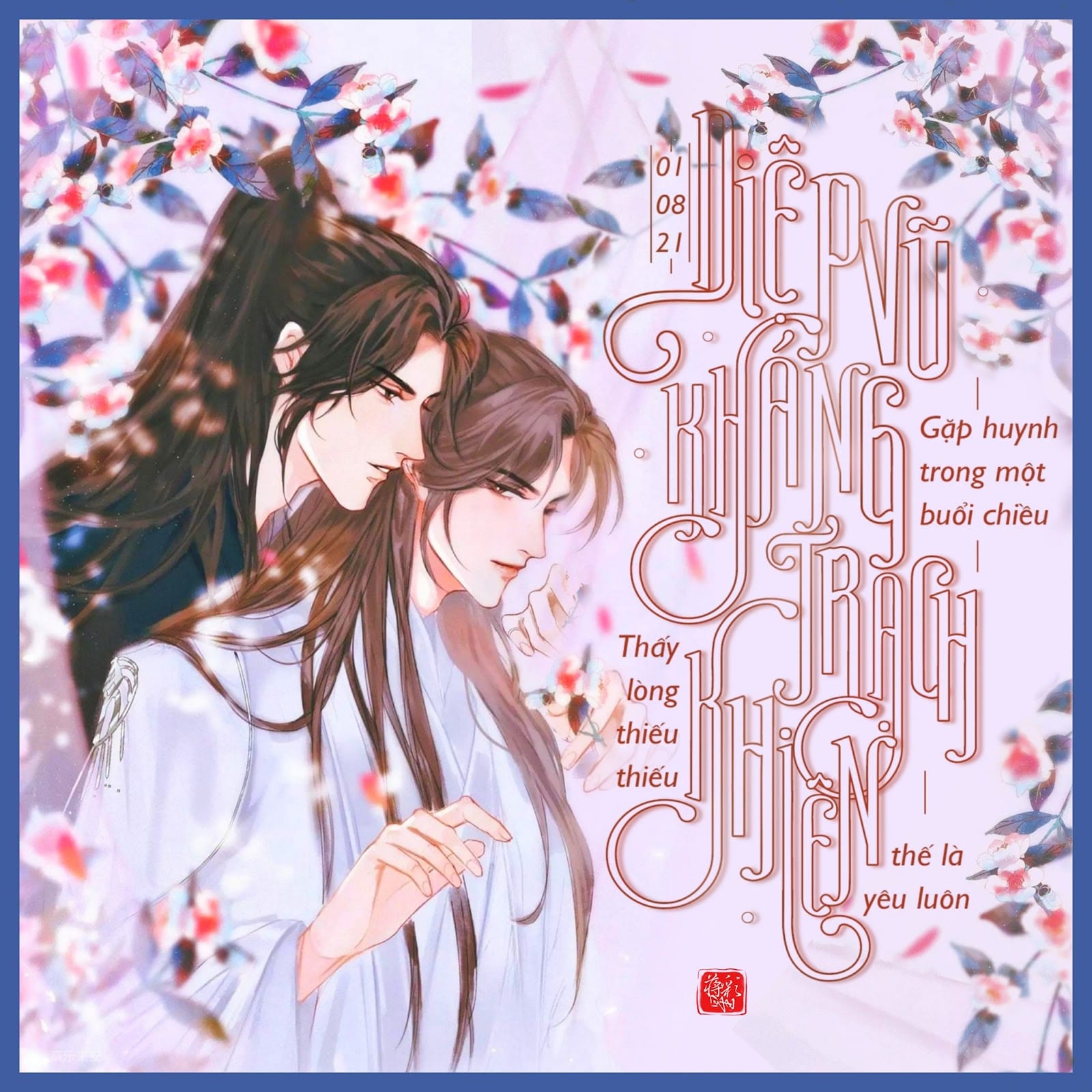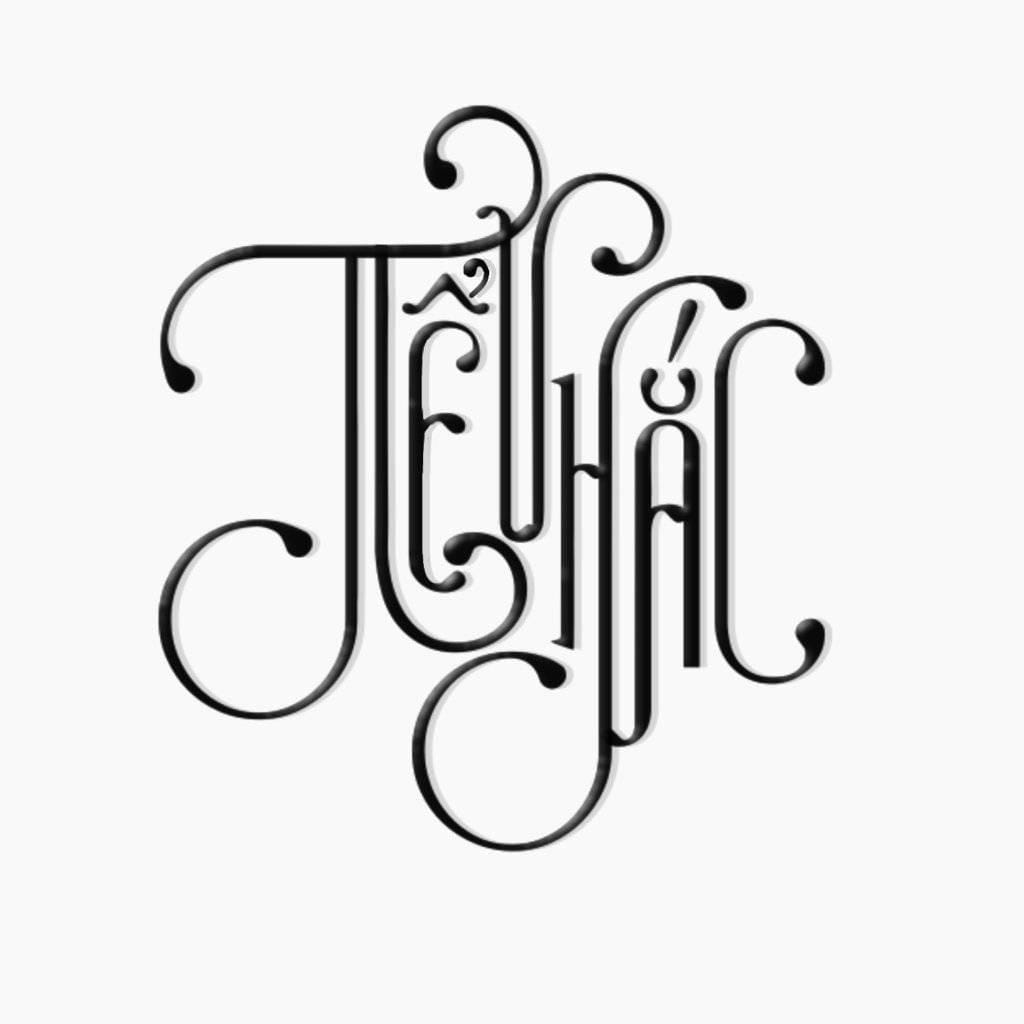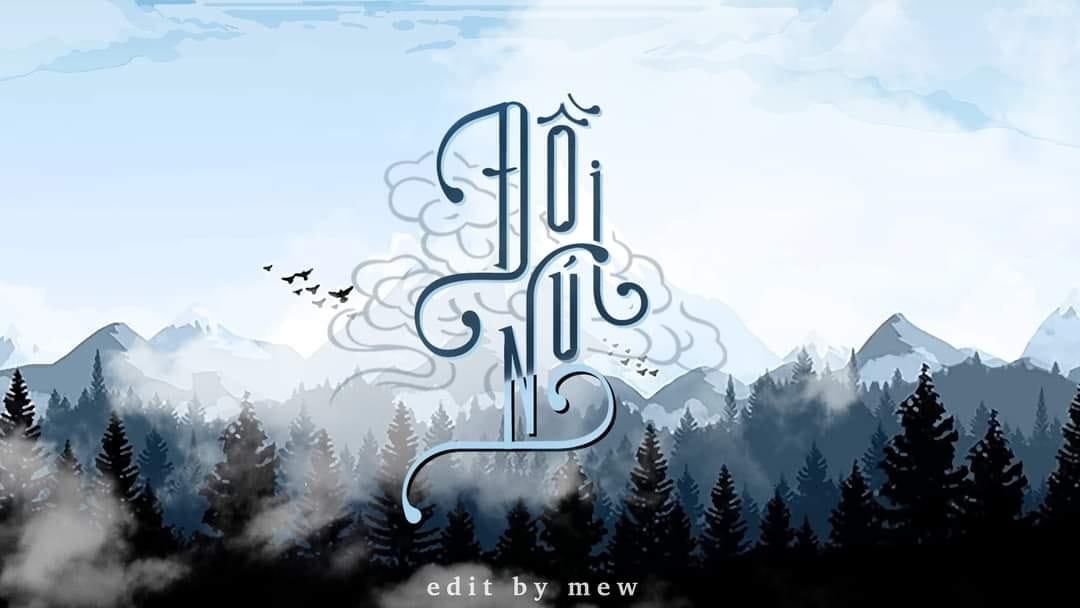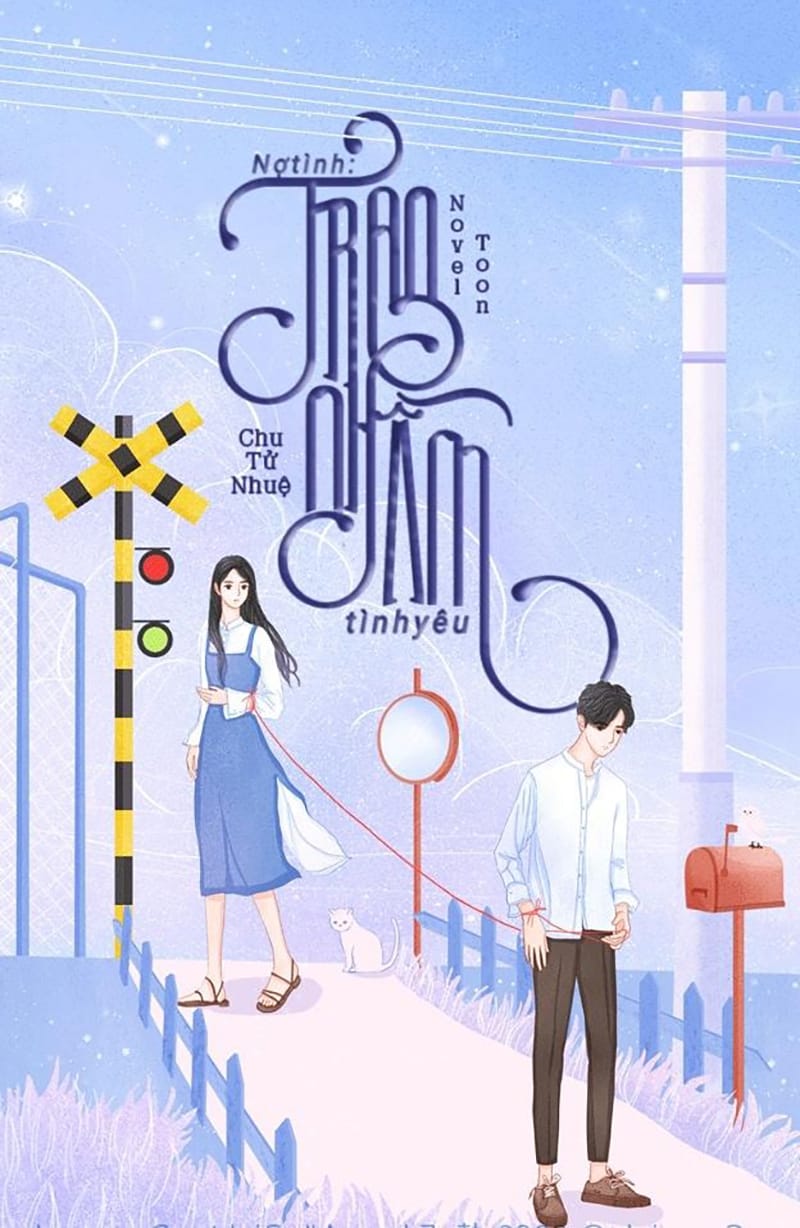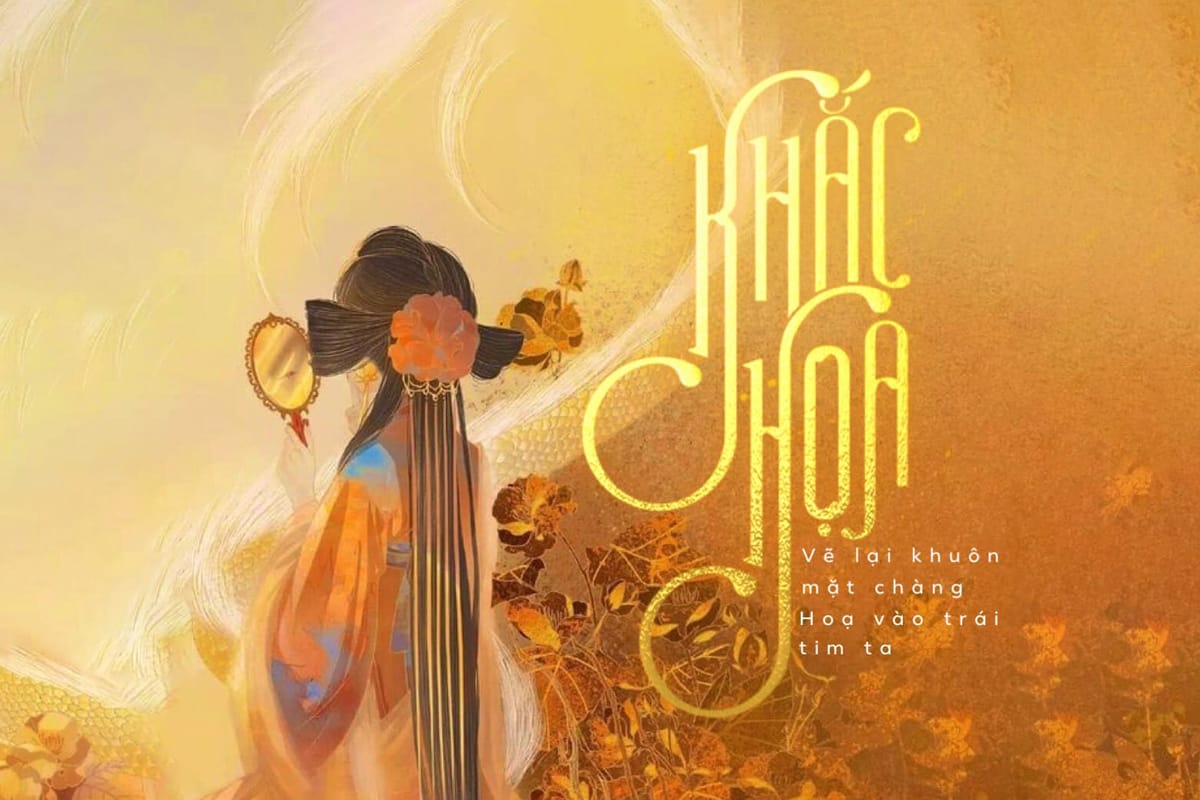
Font Neo Orient Type Việt Hóa là một phông chữ mạnh mẽ với các nét chữ được thiết kế uốn lượn ấn tượng rất phù hợp cho các thiết kế như tiêu đề, bìa truyện, typo… Bạn nên kết hợp các chữ hoa và chữ thường để tạo ra các tác phẩm đẹp như demo dưới nhé.